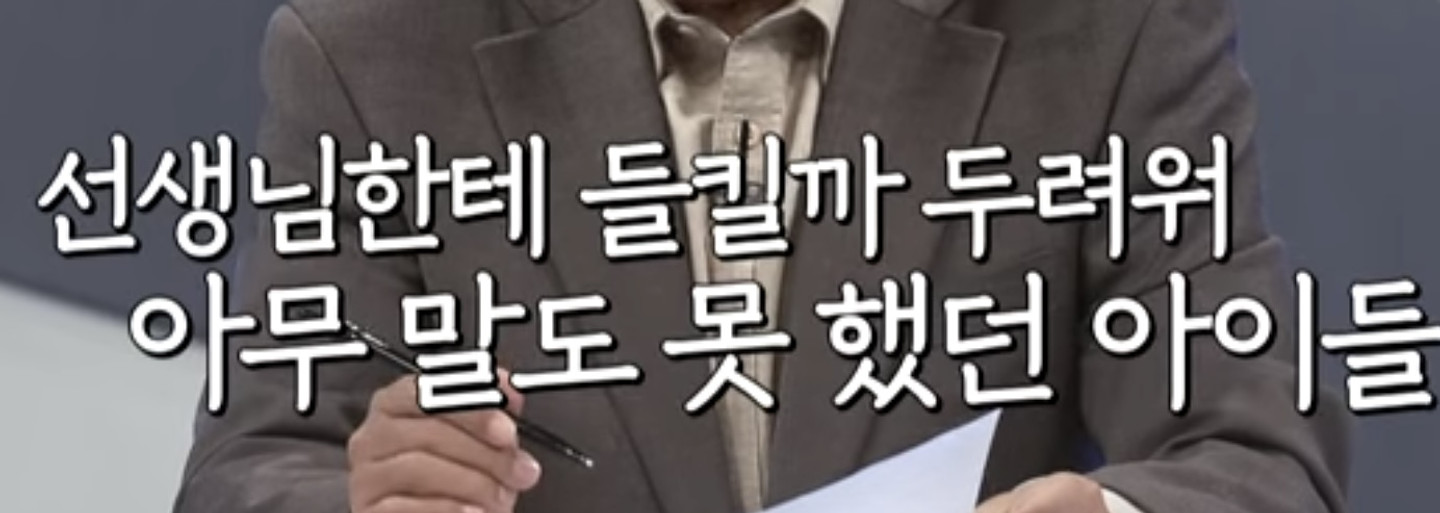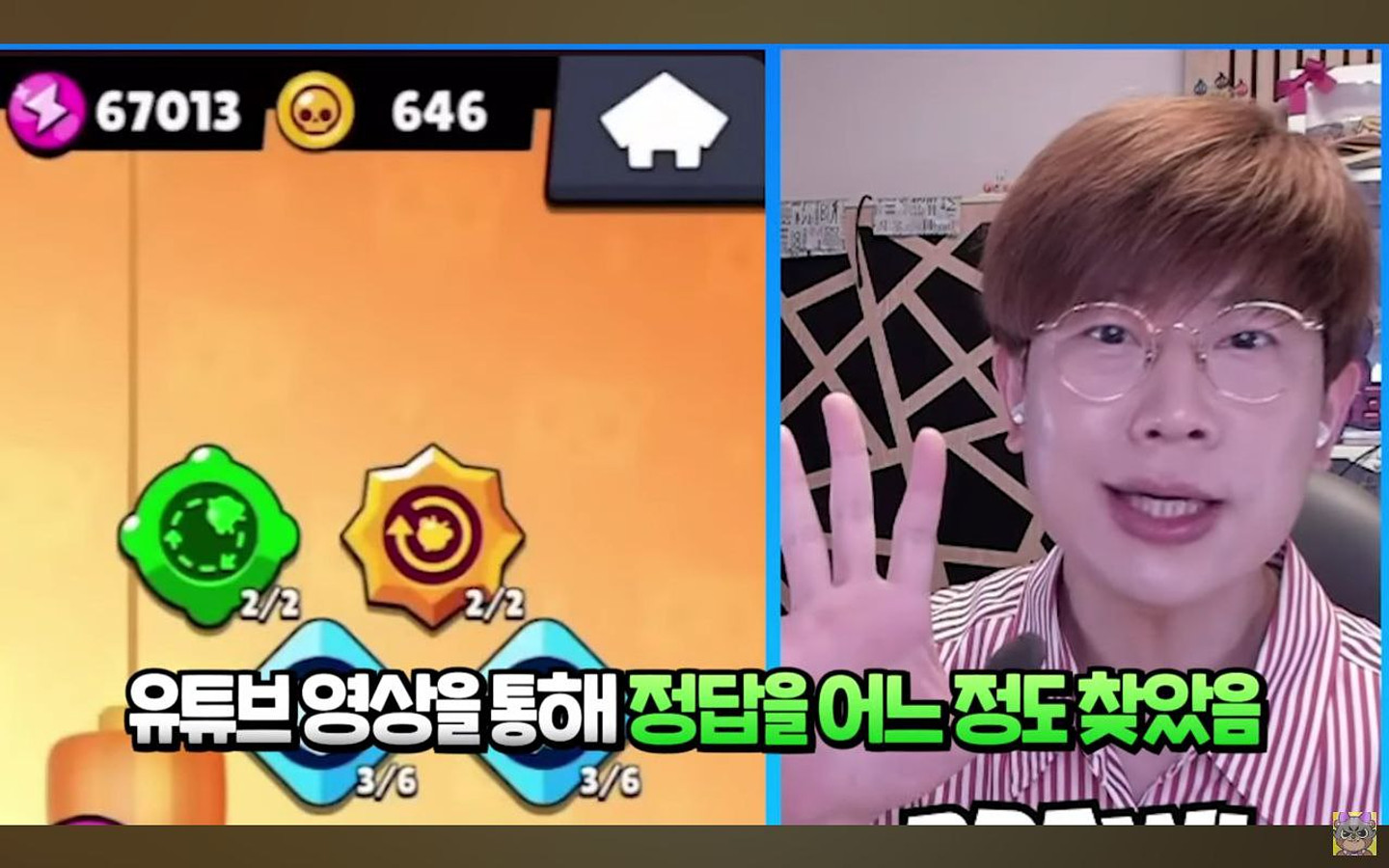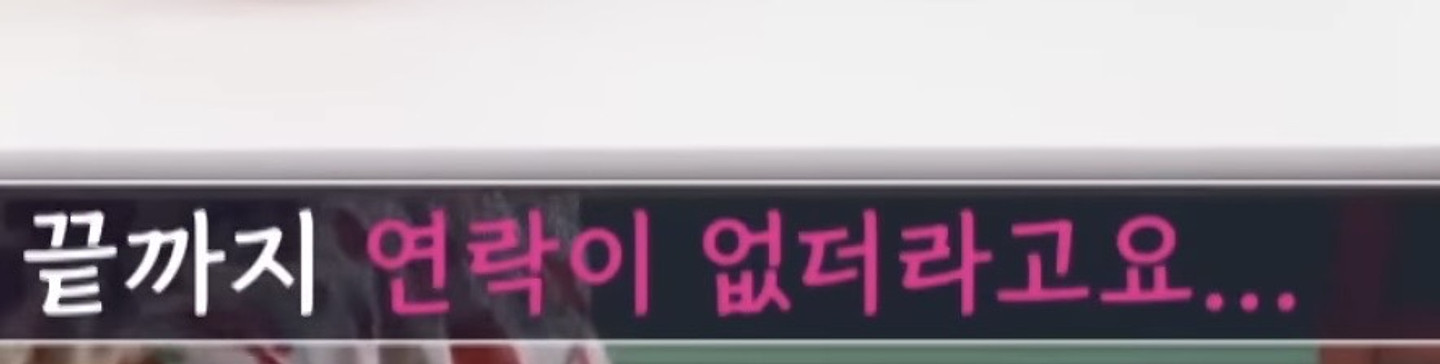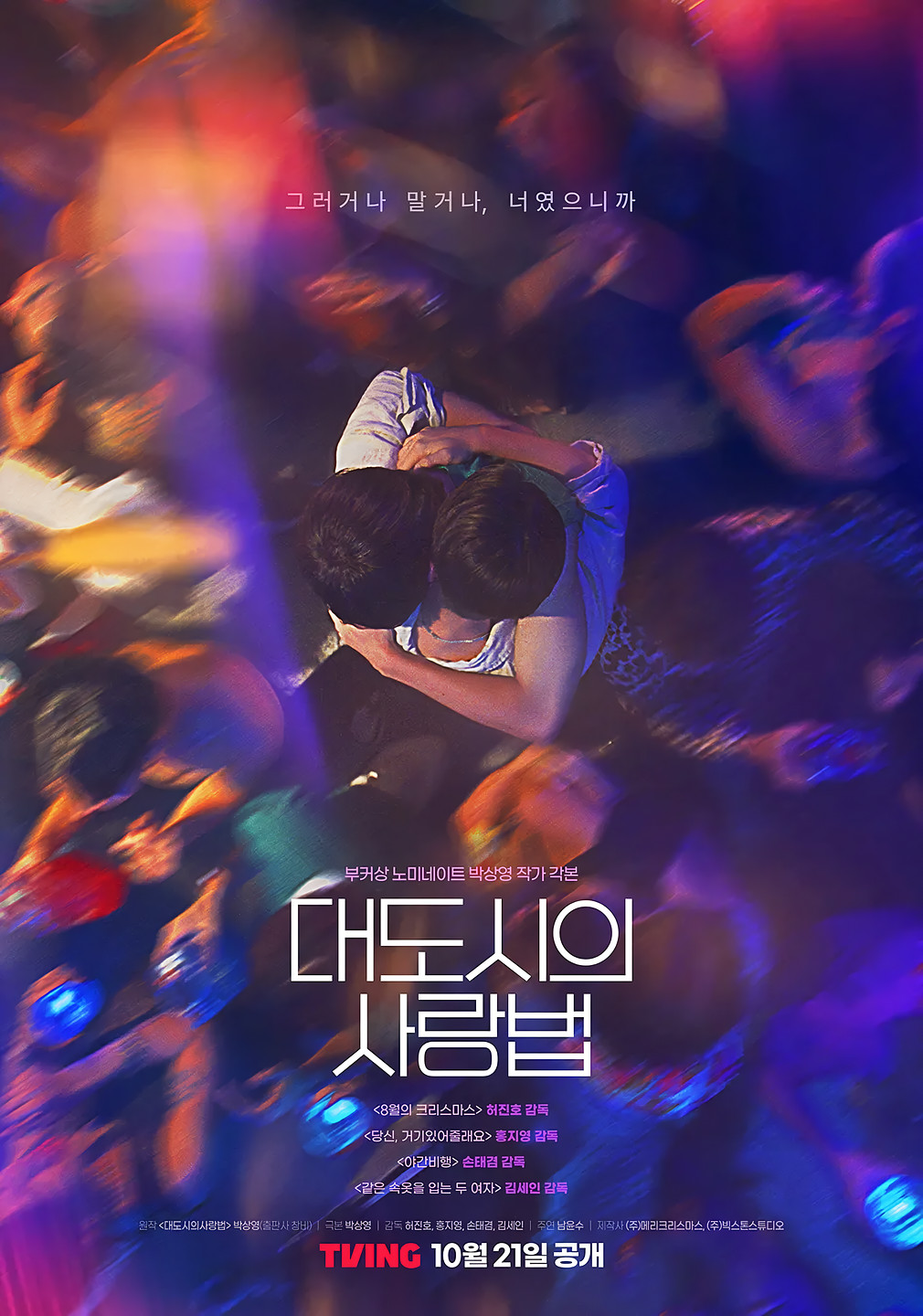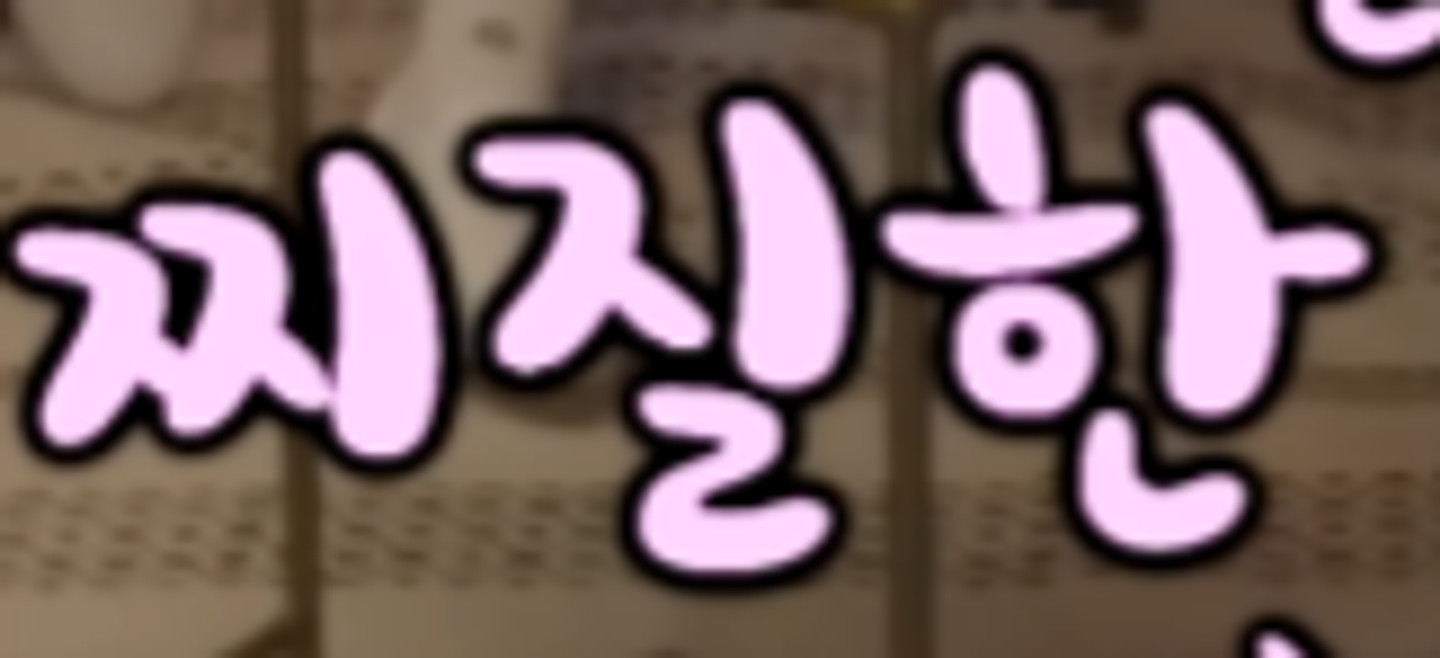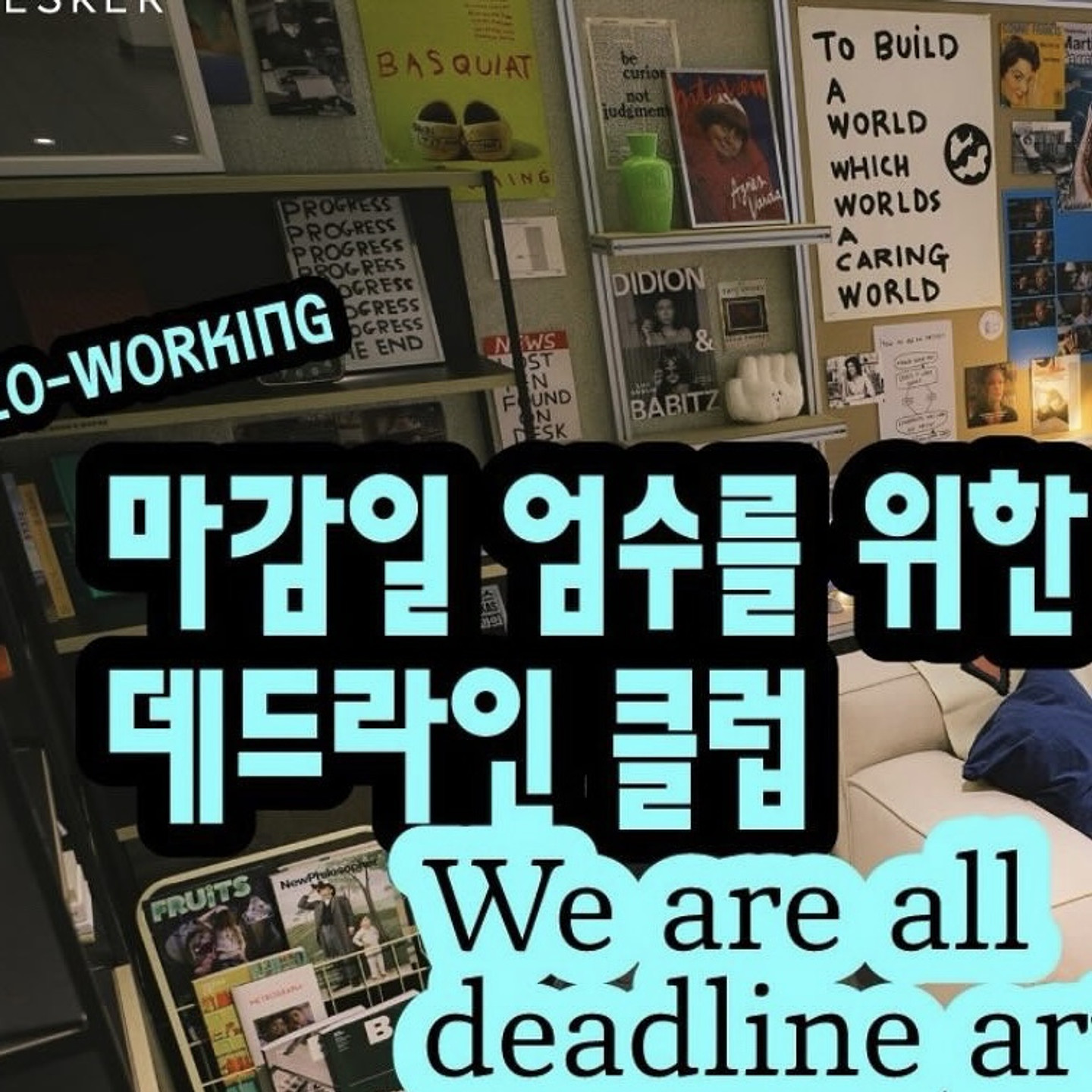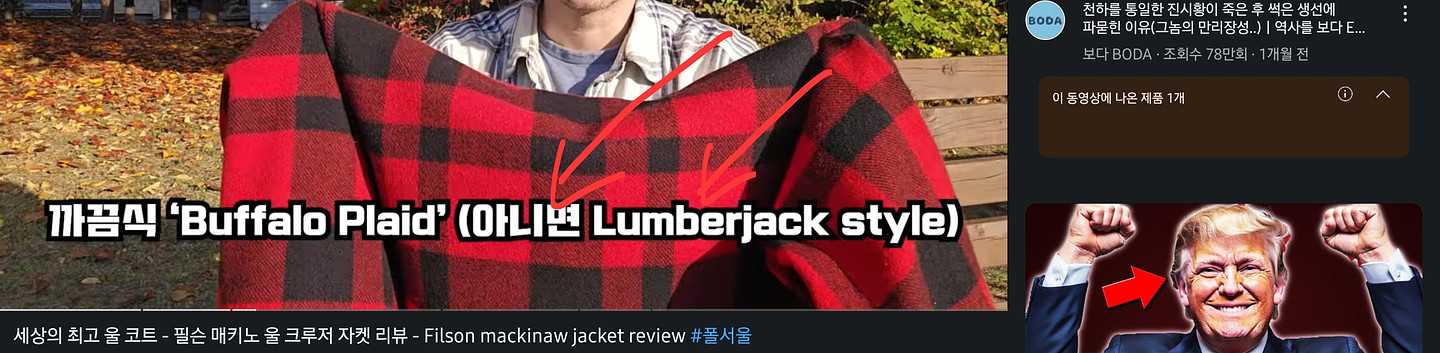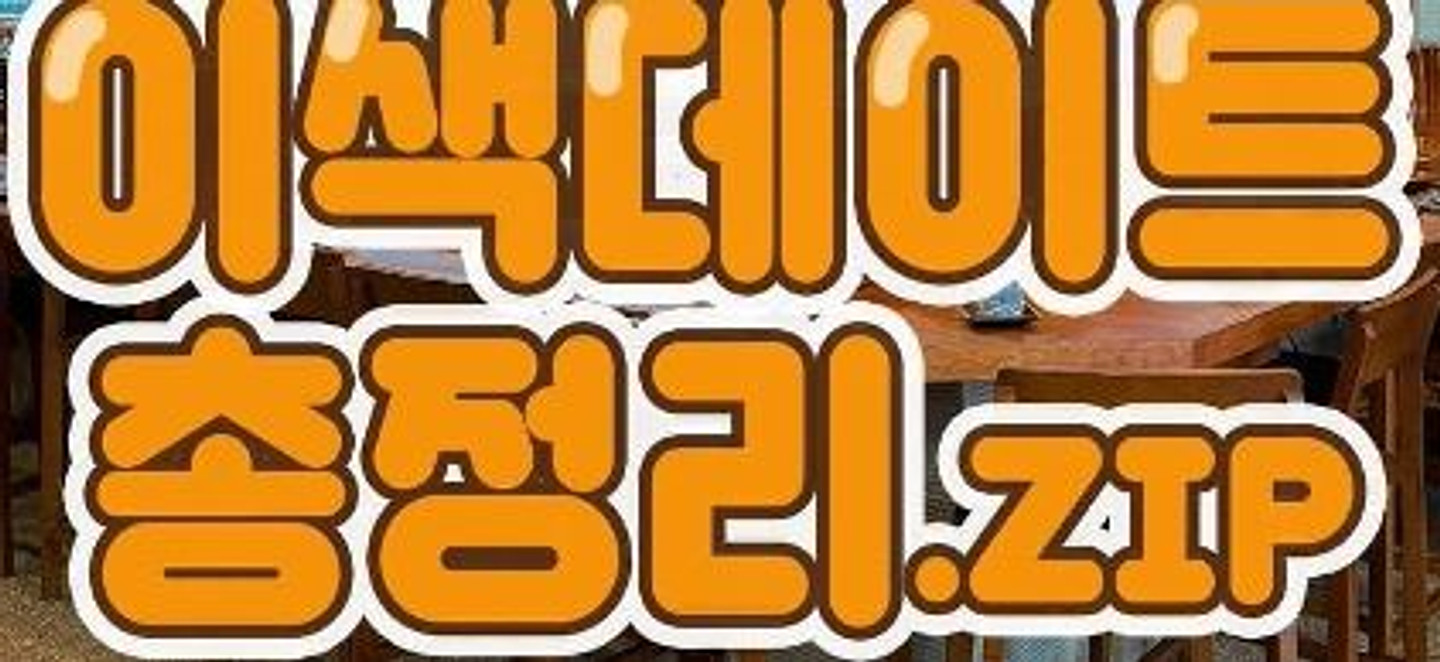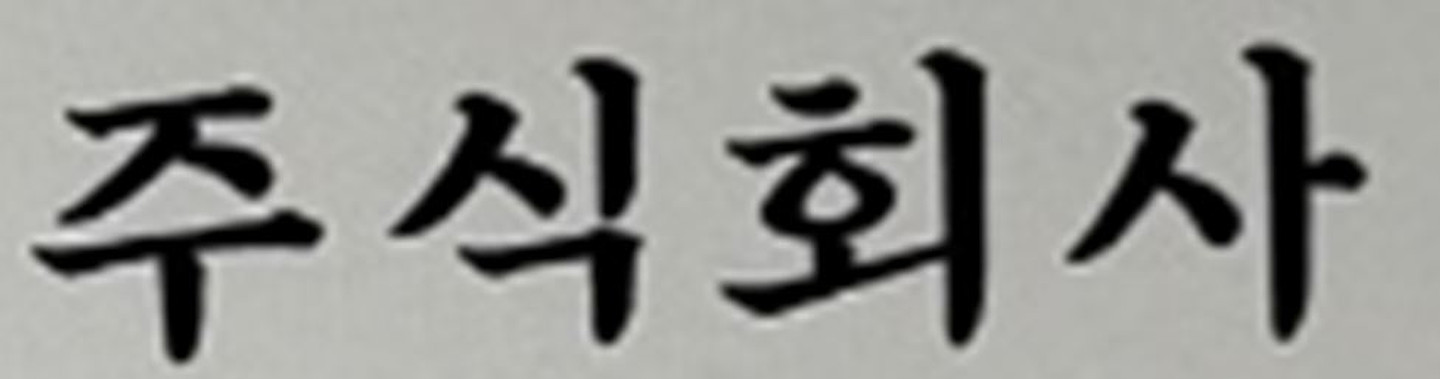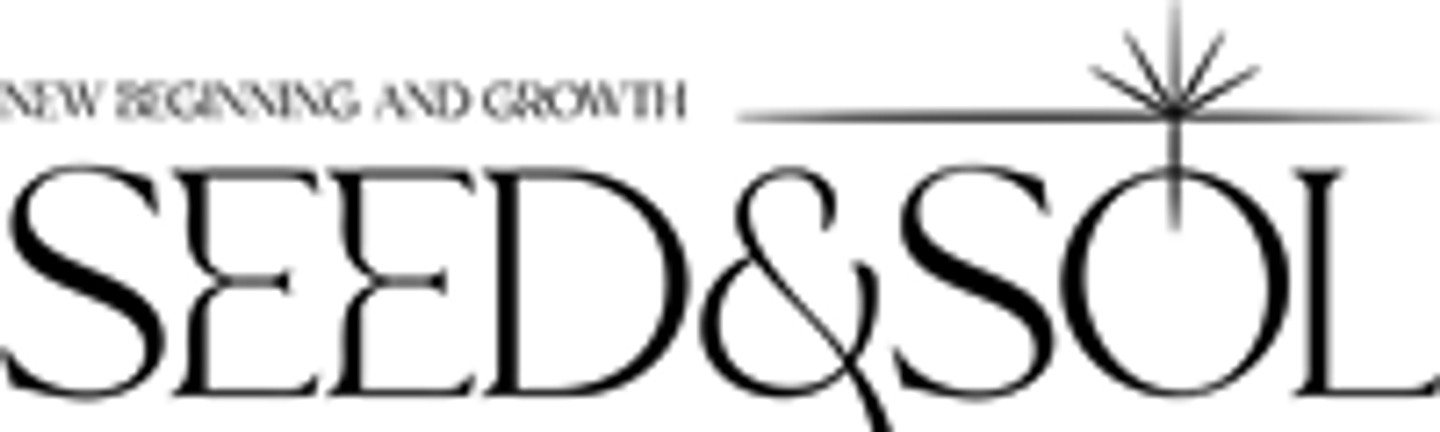
이 폰트 한솔다움체인데 이거랑 비슷한 폰트 뭐가 있을까요 ㅠㅠ
유투브 때잉 영상인데 자막 폰트 뭘까요 ㅜ
딱 떨어지는 고딕체에 ㅅ 이 포인트
이 폰트 뭘까요??
가운데 ALL STAR GAME이라 적힌 부분과 비슷하거나 동일한 폰트를 찾습니다.
글씨체 궁금해요~
이 폰트 정말 알고 싶습니다
family sale에 쓰인 폰트가 도대체 뭘까요?
이 글씨체 뭘까요?
폰트 이름 알려주세요~
이 폰트 이름 뭔가요??
이 글씨체 무엇일까요? 가르쳐주시면 감사하겠습니다 ^_^
폰트 이름 알고 싶어요.
환경운동연합 폰트는 혹시 무엇일까요?
혹시 HY동녁 폰트와 유사한 폰트 있을까요? 있으면 알려주세요
이 폰트 무슨 폰트일까요,,
폰트가 궁금합니다~ 알고 계시면 알려주세요 감사합니다.
약간 시원한 느낌
Vin.T Design 폰트가 뭘까요?
이 글씨체알수있을까요?
독특한 이 폰트 아시는 분 부탁드립니다~
첫구매~ 이 폰트와 위에 신규회원을 위한~ 이 폰트가 같은거 같은데 폰트 이름이 궁금합니다!!
서체가 뭘까요??
세븐틴 코인노래연습장 간판은 무슨 폰트인가요?
이 폰트는 무엇인가요? 약간 기울어보이는데
이 폰트 무엇일까요?
이폰트 궁금합니다!
이 레트로 폰트 뭘까요??
이 폰트 대체 뭘까요?? 알려주심 감사하겠슴다!
무슨 폰트인지 궁금합니다! 🥲
무슨 폰트인지 궁금해요~ㅠㅠ!
위의 세명조랑 비슷한 폰트 있을까요? 많이 얇은 명조체 찾는데... ㅠㅠ 찾기가 어렵네요. 도움을 요청합니다.
이 폰트 좀 알려주세요!
이 폰트 진짜 뭘까요 ㅠㅠ
이 폰트 이름이 뭔지 부탁드립니다. T-T
이 폰트 알려주세요!
살롱드 서울 무슨폰트인가요
저 소제목 폰트 아시는분있나여
이건 어떤 폰트인지 알 수 있을까요? 숫자와 글자 다른거긴 한거 같은데
이 숫자 폰트가 뭔지 궁금합니다
폰트 궁금합니다!!!
궁금해요 ㅜㅜ
폰트가 궁금합니다! 도와주세요!
이거 알려듀데요
이거 무슨 폰트인지 아시나요ㅠㅠ
큰 제목 폰트 궁금해요
요거 폰트가 뭘까요?ㅠㅠ
이 폰트가 뭔지 아시나요?ㅜ
이 폰트 뭔지 궁금합니다
이 폰트 무엇인가요?
이폰트를 쓰고 싶은데 아무리 찾아도 안보여요ㅠㅠ 제발 찾아주시면 감사하겠습니다
이 폰트 뭔지 알려주시면 감사하겠습니다.